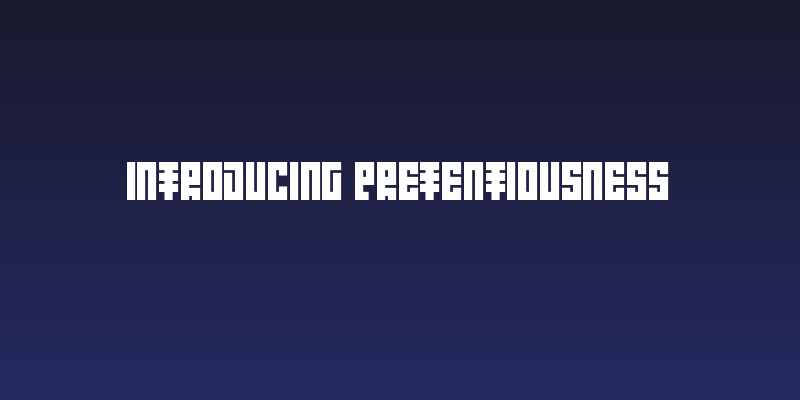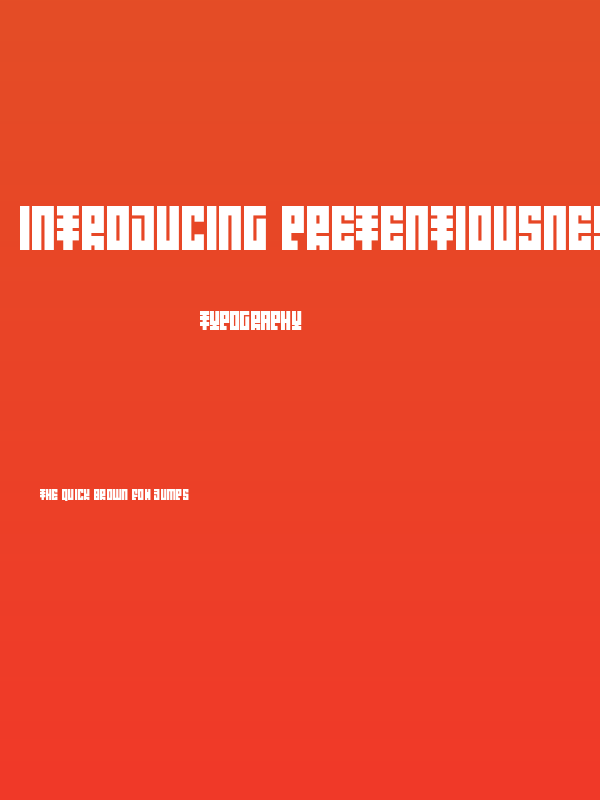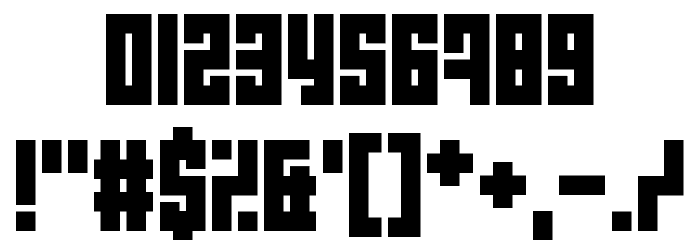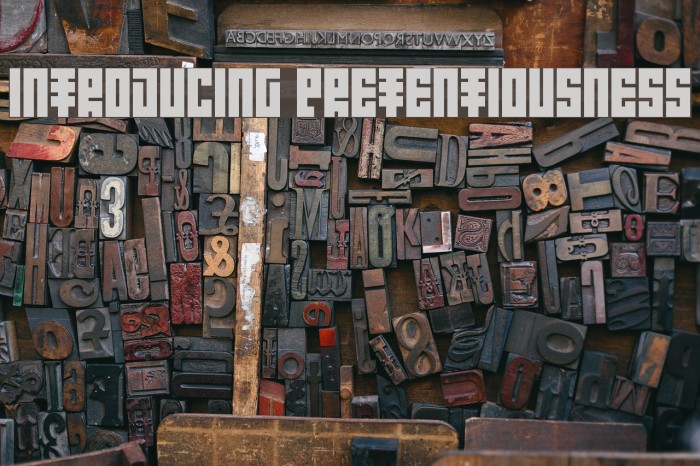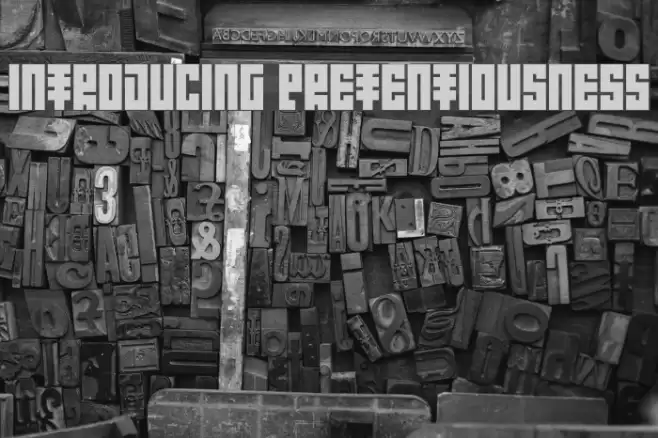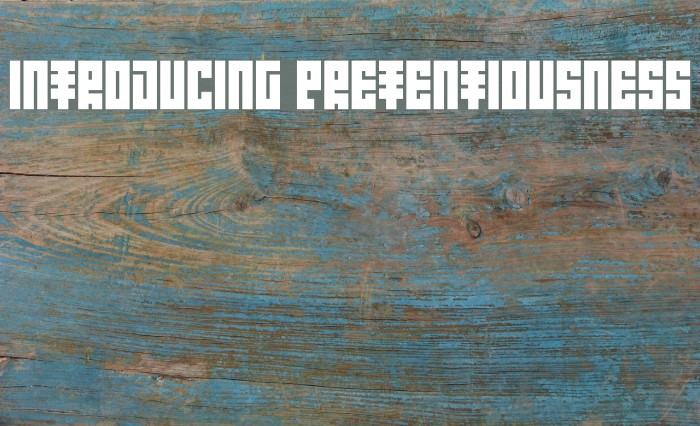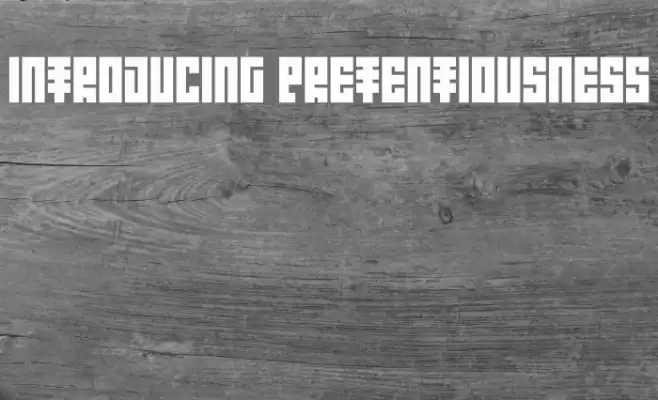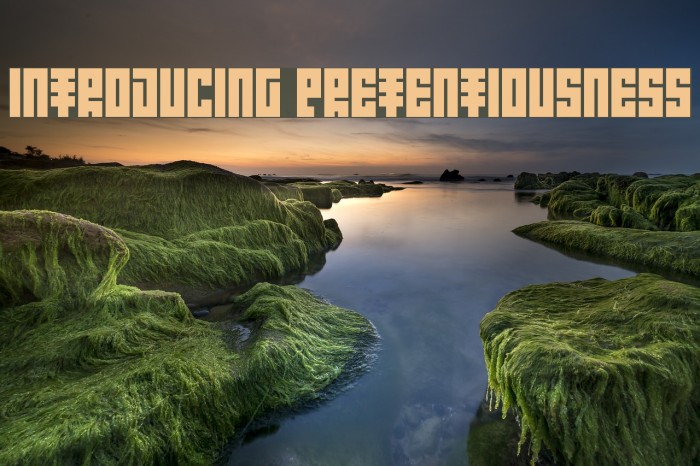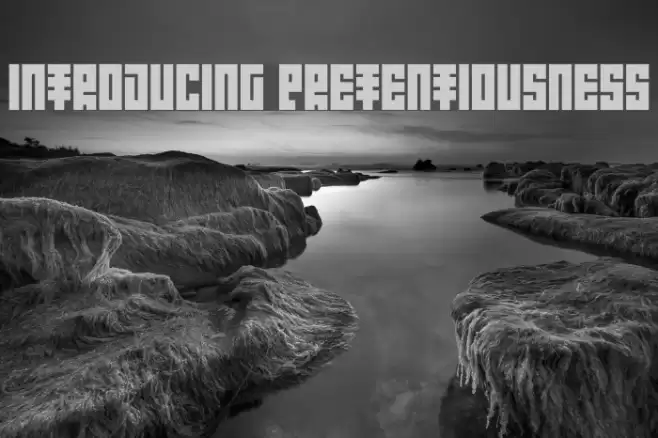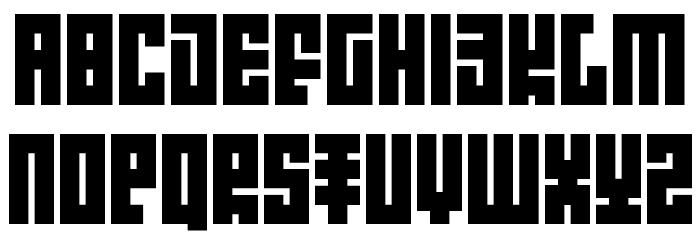
Introducing Pretentiousness Font
| Caso de uso | Logos, Headlines, Posters |
| Proyectos propuestos | Ideal for video game design, tech branding, digital art projects, and futuristic-themed posters. |